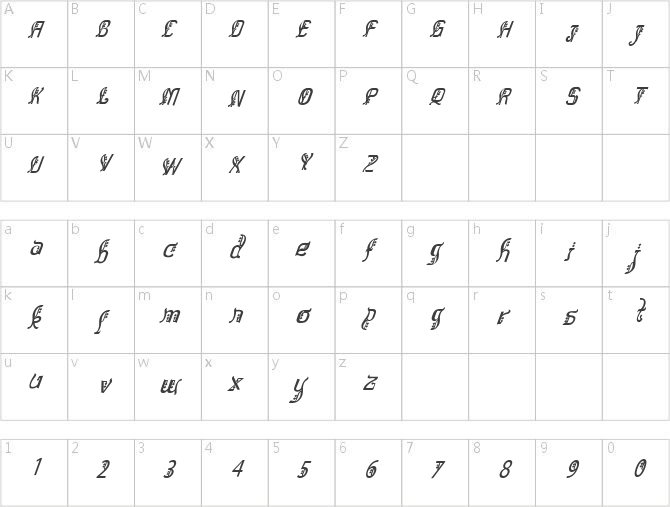
字體名稱: Bitling
Bitling sulochi calligra
Bitling sulochi calligra介紹
Bitling sulochi calligra字體字庫是一款讓人賞心悅目、百看不厭的英文字體,適合各類廣告和產品包裝設計應用,字體大小0.04MB,格式為ttf字體,上傳用戶是釜源貿易,作者/版權方為未知